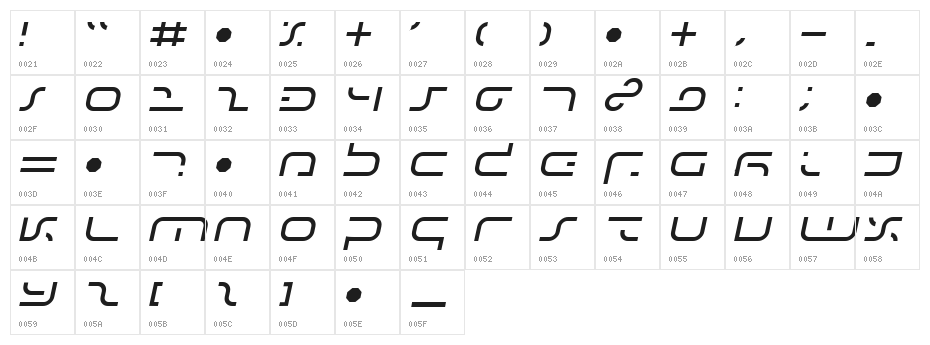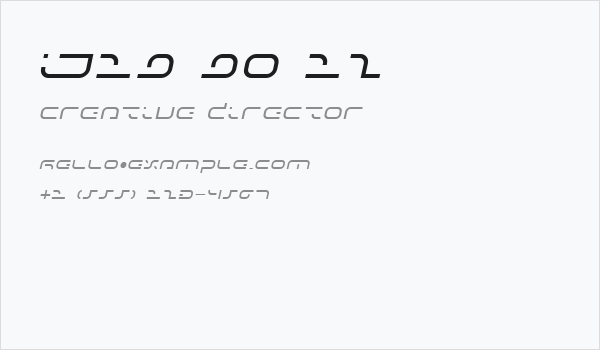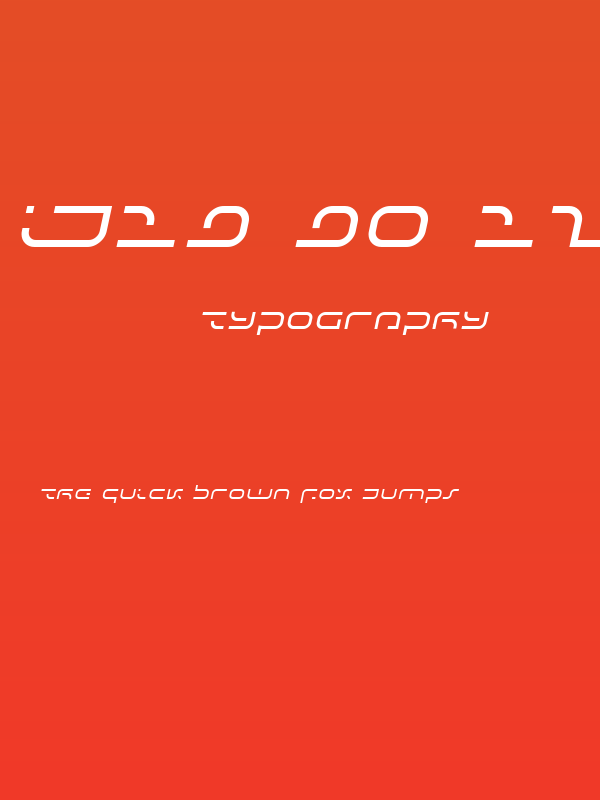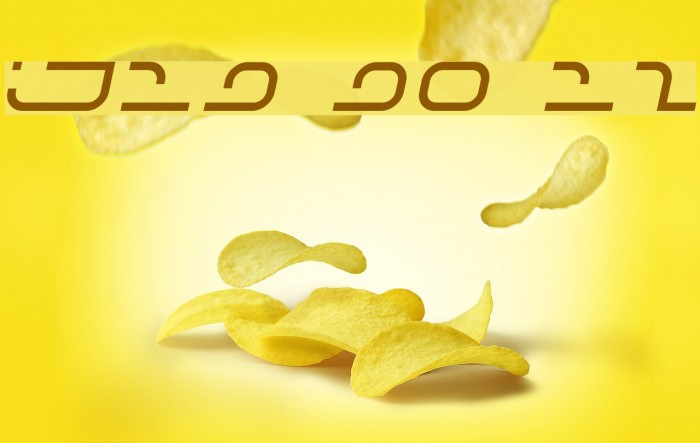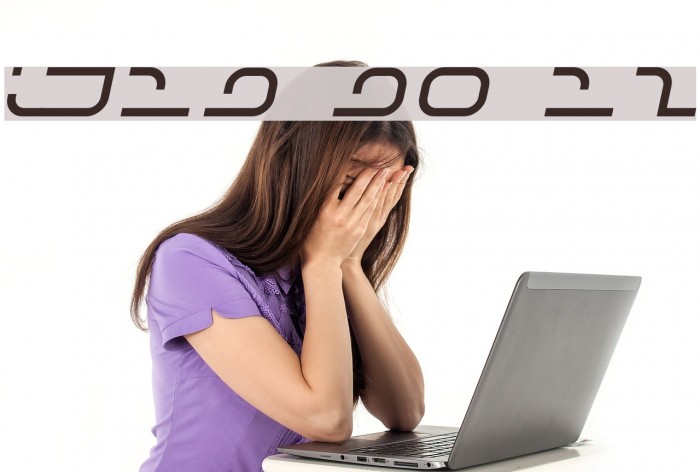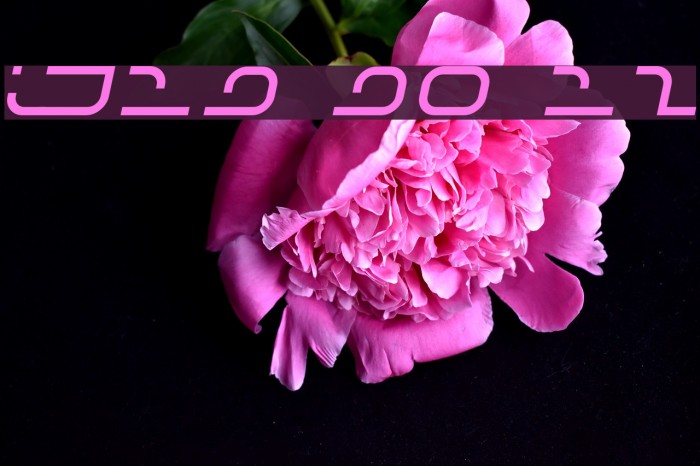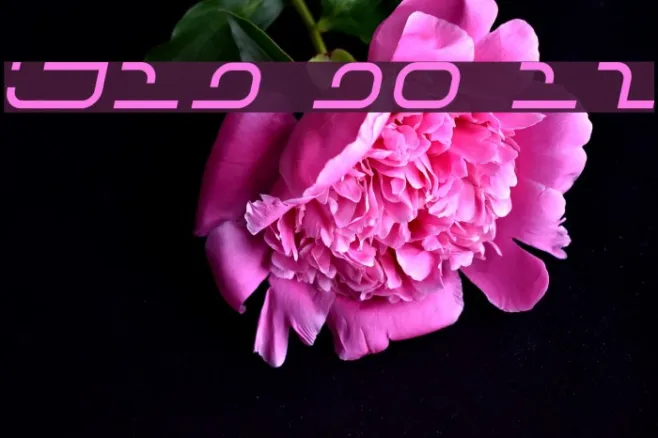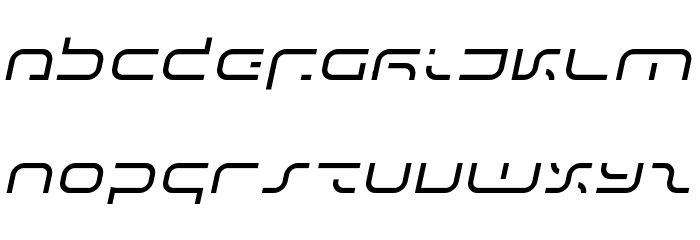
IJ19 90 12 Font
| Nom | IJ19 90 12 |
| Style général | Futuristic, Geometric |
| Cas d'utilisation | Headlines, Logos, Digital Interfaces |
| Projets proposés | Ideal for technology branding, sci-fi themes, modern digital interfaces, and innovative design projects. |